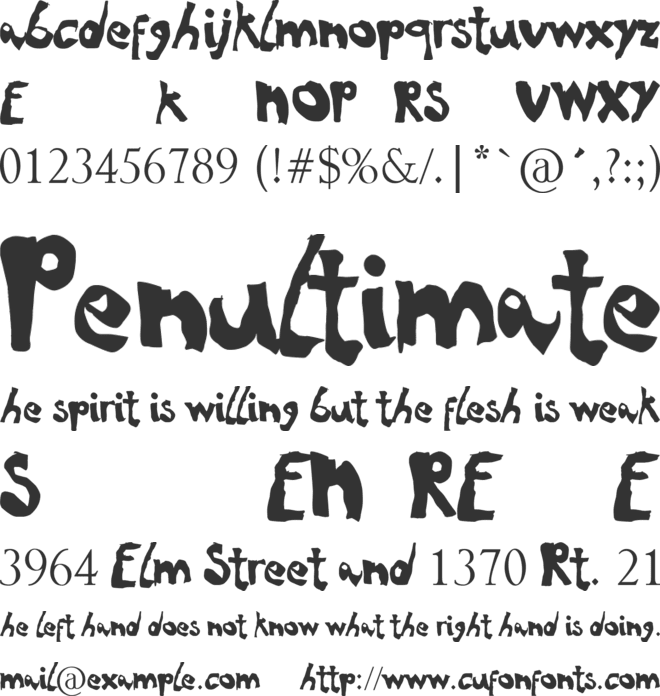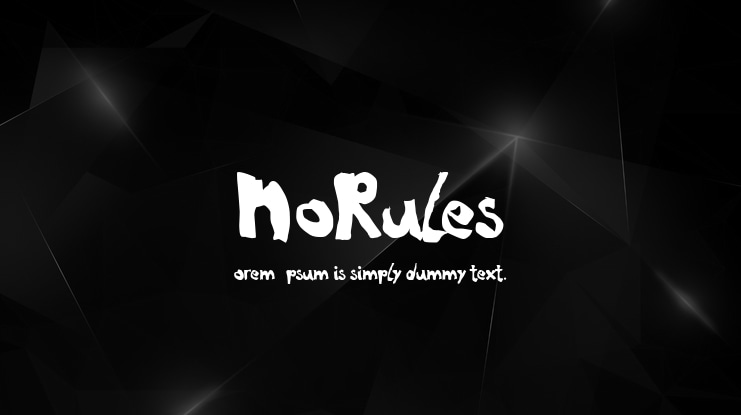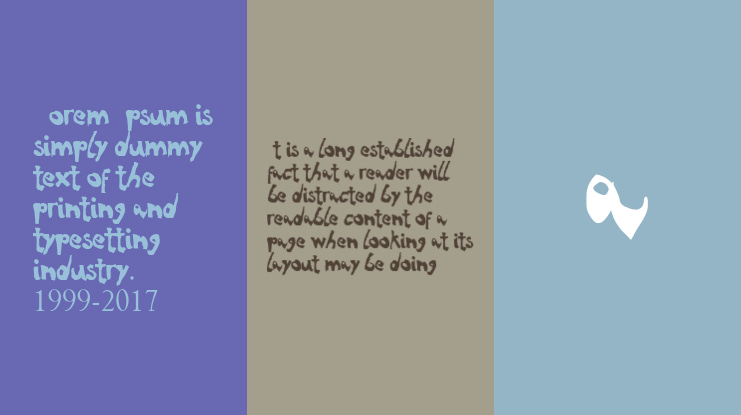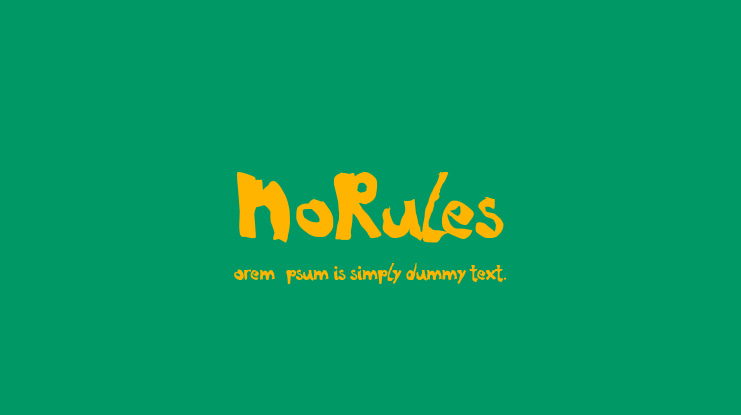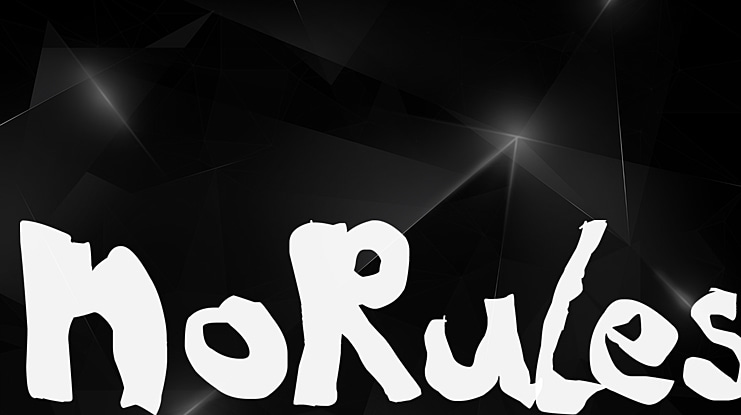
NoRules Font
NORULES: sin reglas, informales, locas, desenfadadas, distintas, desiguales, personales, feas? rompedoras. En prueba, inacabadas. Testing. enero 2012 / Minúsculas completas / Faltan Mayúsculas y Números.
Fueron creadas para unos dibujos personales un poco locos. Las dibujé con la mano izquierda y los ojos cerrados.